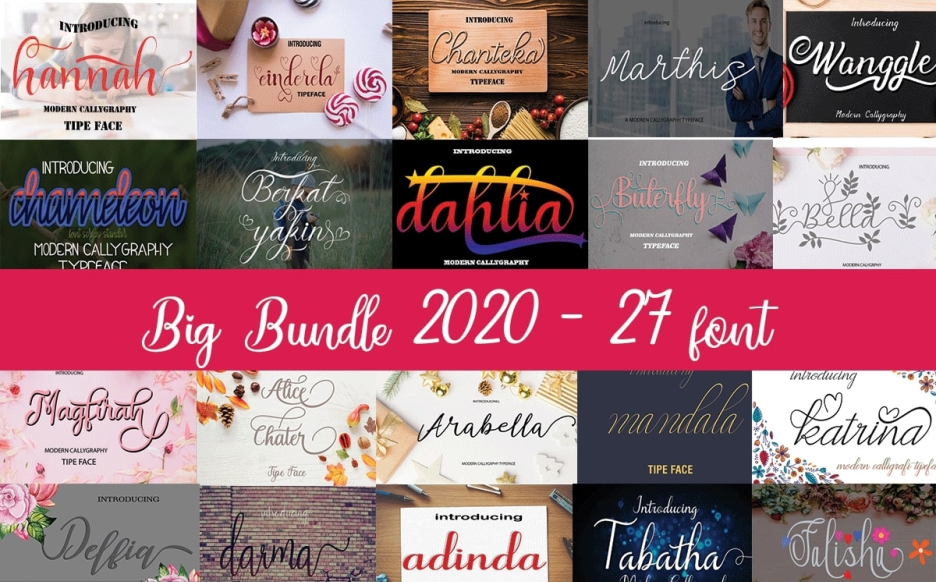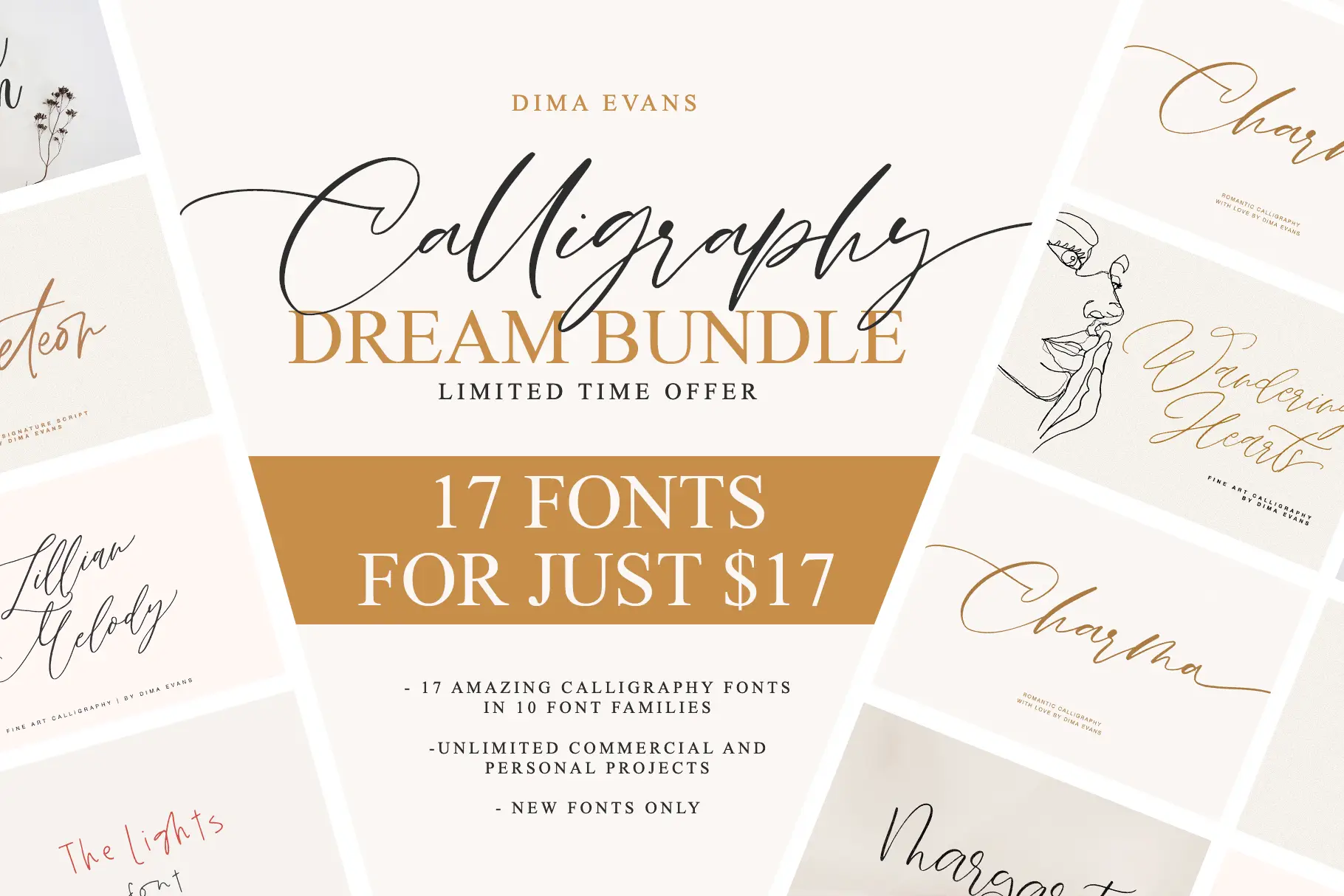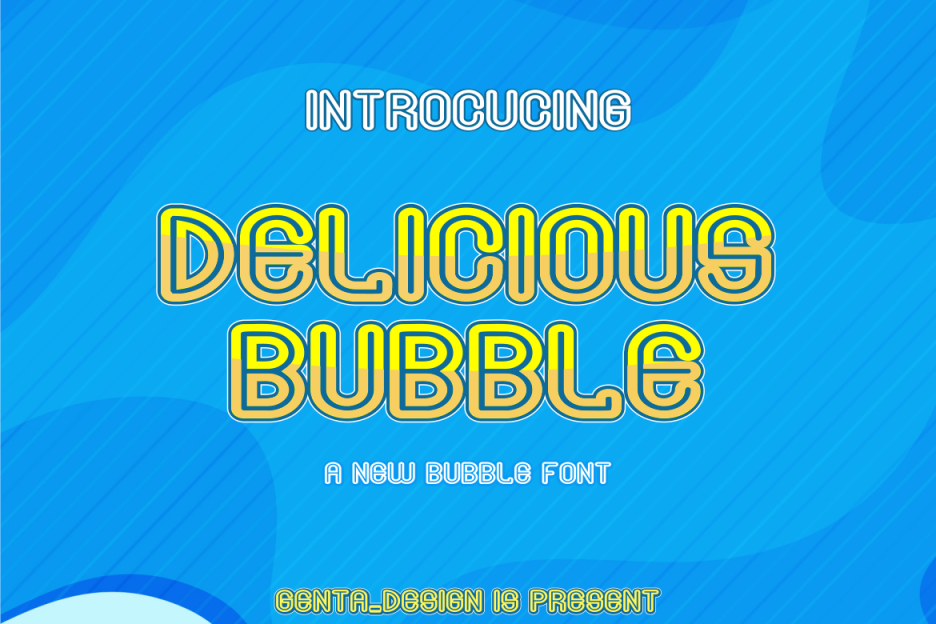
20个必拥有的字体包,来自Brushespack系列第164部分 ✨🎨
你好,充满创意的灵魂!👋 你是否曾盯着空白的画布,只希望拥有一款*完美*的字体来将你的愿景变为现实?无论你是经验丰富的平面设计师,还是刚刚起步的充满激情的数字艺术家,拥有一个超棒的字体库就像拥有一种秘密超能力。🚀
我们深入挖掘了Brushespack系列第164期,为你带来了20套绝对惊艳的字体组合,它们将彻底改变你的项目。从俏皮可爱的手写体到大胆现代的展示体,再到优雅的书法体,这份清单涵盖了各种风格。准备好让你的设计水平更上一层楼吧!🎨✨
为什么要使用这些字体组合?
说实话——找到真正能搭配使用的高质量多功能字体,简直是改变游戏规则的大事。这些字体包不仅仅是多了几个字母,它们能为你省去数小时的搜索时间,让你拥有混搭和实验的创作自由。无论你是在打造品牌形象、设计婚礼请柬,还是搭建令人惊艳的网站,这些精心策划的合集都能确保你的排版始终恰到好处。💥
20大精选字体包推荐
现代展示字体包
从重磅选手开始吧!这款字体包是你打造时尚现代标题的首选。从优雅到粗犷的风格一应俱全,非常适合让你的标志和海报脱颖而出。🚀
Deliciousbubble 可爱字体 3B3Ba8J
Deliciousbubble Cute Font 3B3Ba8J
这太可爱了吧?!🥹 Deliciousbubble 圆润俏皮的设计充满了纯粹的欢乐。非常适合儿童品牌设计、社交媒体图形,或任何需要友好、活泼个性的场景。
可爱友好字体合辑
温暖与个性?算我一个!这个合辑融合了手写体、无衬线体和显示字体,风格超级亲和。非常适合需要温馨感的标志、网页内容和印刷物料。🤗
可爱俏皮字体合辑 – 24款高级字体,价值$
可爱俏皮字体包 – 24款高级字体,价值$
二十四款高级字体?!没错,就是它!🎉 从趣味手写体到魅力展示字,这个字体包是任何喜爱设计中带点乐趣的人的宝藏之选。
25款字体大礼包
Big Bundle Of 25 Fonts
需要多样性?这就是你的大奖。这套包含25款独特字体,涵盖优雅衬线体到现代无衬线体,任一场合你都能找到完美的字体。🎯
毛笔字体捆绑包合集
Brush Font Bundles Collections
使用这些独特的毛笔风格字体,增添个性十足的手绘质感。非常适合品牌设计、标志制作以及需要那种真实、不完美却恰如其分的项目。🖌️
Creativemarket – 2019年黑色星期五促销
Creativemarket – Black Friday Sale 2019
来自过去的经典,至今仍是宝藏!这套合集包含高质量字体、图形和模板,完美适用于任何设计项目。真正的全能选手。🎁
Carmenta – 签名字体 2N6Gvvh
Carmenta – Signature Font 2N6Gvvh
优雅的极致定义。💫 Carmenta 字体流畅的笔画与优美的草书设计,使其成为邀请函、奢侈品牌和高雅标志的绝佳之选。
西里尔字体套装 – 11款高级字体
Cyrillic Font Bundle – 11 Premium Fonts
多样性很重要!🌍 此字体系列包含11款优质字体,风格涵盖衬线体到展示字体,全部支持西里尔字符。国际项目的必备之选。
可爱字体组合包
可爱字体套装
一个充满魅力的套装。从奇特的书写体到粗体展示字,这个系列充满了个性,完美地为你的作品增添那份额外的快乐。🥰
书法字体套装
Calligraphic Fonts Bundle
极致的优雅。这组精心挑选的书法字体合集,完美适用于婚礼请柬、高端品牌设计,以及任何需要增添格调的设计项目。🕊️
大合集字体包
Big Collection Font Bundle
精选多样化高品质字体,涵盖衬线体、无衬线体、手写体等。这是设计师必备的终极工具包,为任何项目提供可靠的字体选择。🧰
书法手写字体合集
书法手写字体套装
喜欢手写文字的外观但又想要数字便利?这款套装模拟了精美的手写书法,非常适合增添个性与艺术感。✍️
可爱字体套装 – 44款高级字体现价$
可爱字体合集 – 44款优质字体价值 $
四十四种字体?!🤯 这可是一座可爱宝藏!从俏皮手写体到优雅衬线体,应有尽有,你再也不用担心找不到可爱的选择了。
大型字体包
Big Fonts Bundle
让你脱颖而出!🗣️ 这套字体全是醒目、富有表现力的字体,能瞬间抓住眼球。非常适合标题、海报以及任何需要引人注目的设计。
展示与手写字体合集
Display & Script Font Collection
完美组合!此合集将优雅的手写字体与醒目的展示字体配对,为您提供在设计中打造惊艳对比的终极工具包。🎭
书法字体特别组合包
Calligraphy Special Bundle
这不仅仅是字体!此特别套装包含装饰元素和模板,以及精美的书法字体。它是创作惊艳艺术版面的完整工具包。🎨
Facility 字体合集套装 – 22款字体
Facility The Collection Font Bundle – 22 Fonts
精选22款独特字体,从优雅衬线体到现代无衬线体,一应俱全。该字体包提供了极大的灵活性,是您设计库中的必备之选。📚
涂鸦字体包
为你的作品注入一丝奇思妙想!这些充满趣味和艺术感的字体,非常适合为你的品牌设计、标志和插画增添独特的手绘风格。✏️
圣诞字体包
圣诞字体套装
感受节日气氛吧!🎄 这套字体合集包含了充满节日气息的手写体、衬线体和无衬线展示字体,非常适合用于圣诞贺卡、季节性营销以及温馨的节日设计。